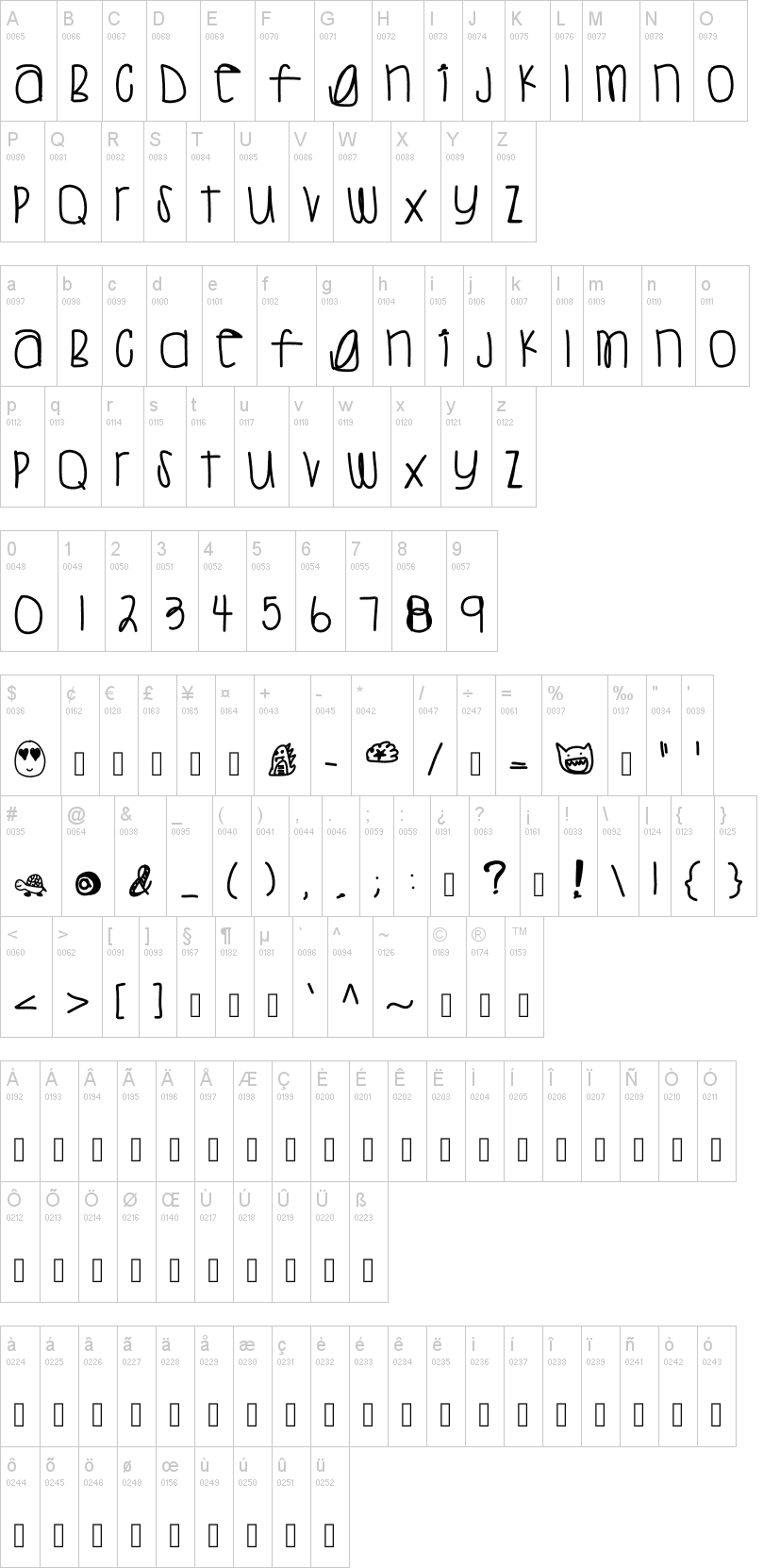
Sweet Tea
Sweet Tea 是一种手写风格的字体,常用于设计卡片、海报、招贴、餐厅菜单等场合。它的特点是线条柔和,仿佛是用毛笔或者钢笔书写的,具有很强的自然感和人情味。Sweet Tea 字体的字形流畅、舒展,不仅适合传统的手写风格,也很适合现代化的设计风格。此外,Sweet Tea 字体还有多种变体,包括粗体、斜体和粗斜体等,可以满足不同设计需求。
Sweet Tea是一款非常不错的手写艺术字体,具有很好的视觉感,适合于文化类的宣传设计、商业类品牌的广告和产品包装设计以及个性化文字排版等较多场景。